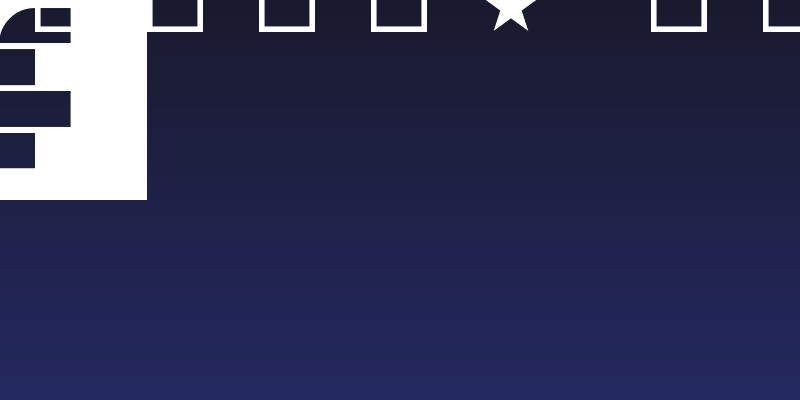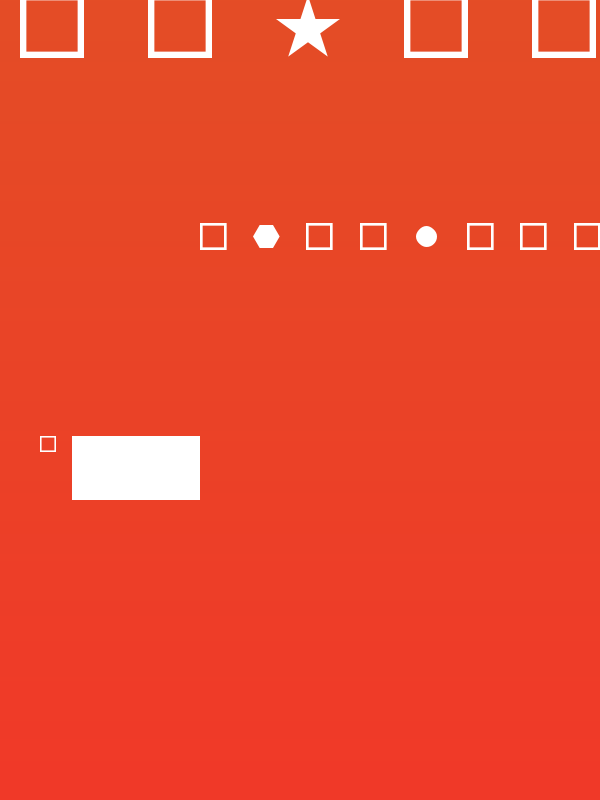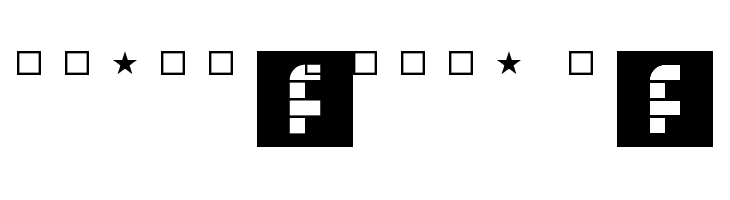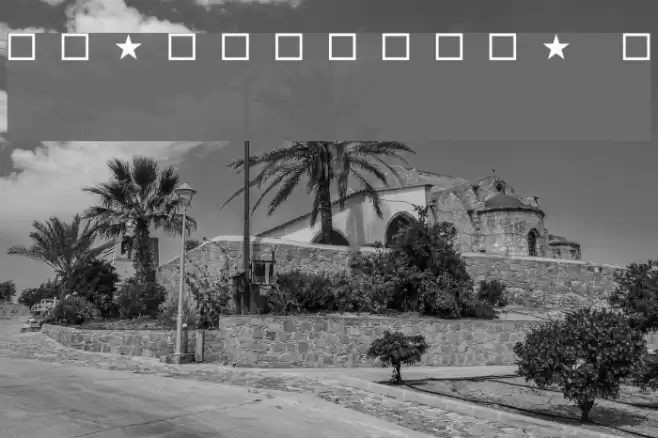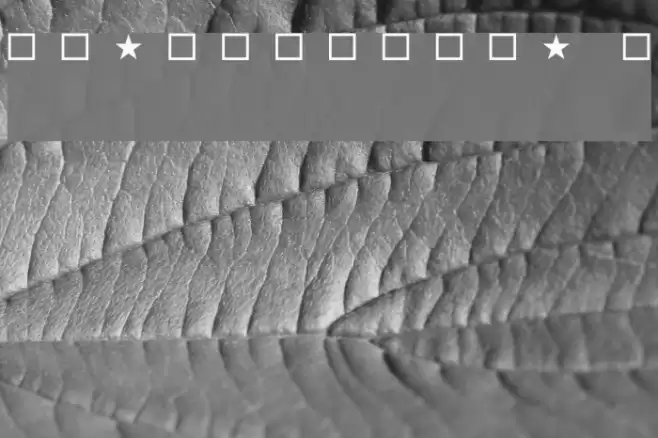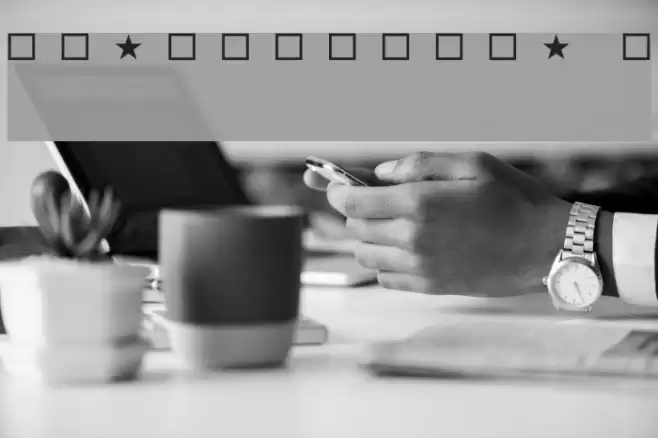
BAZIC_SHAPEZ Regular Font
| Cas d'utilisation | Logos, Posters, Artistic Displays |
| Projets proposés | Ideal for modern art projects, abstract designs, branding for creative industries, and experimental digital media. |